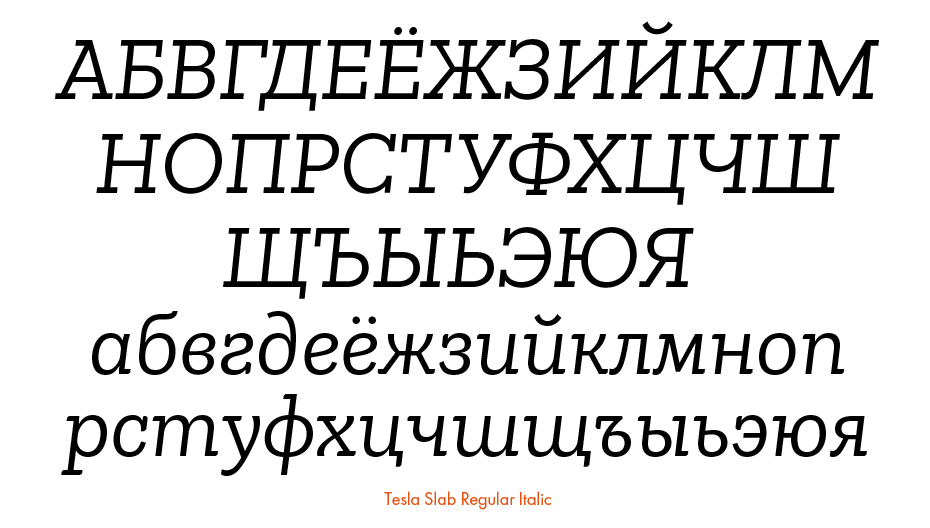
13 потрясающих шрифтовых трендов 2023
То, что вы пишете, важно, но то, как вы это делаете, еще важнее. Типографика — мощный инструмент в руках дизайнера: используйте его правильно, и все обратят внимание, используйте неправильно, и люди просто прокрутят страницу вниз. И хотя навыки проектирования и вкус играют в успехе проекта основную роль, следить за тенденциями важно, нравится вам это или нет. Сегодня мы рассмотрим трендовые шрифты и стили типографики — они уже здесь, и они определенно останутся с нами до конца 2023 года.
Источник: DribbbleЧто такое типографика и почему она важна?
В двух словах, типографика — это то, как ваш текст выглядит на странице/экране/где бы он ни находился. Это искусство настройки различных деталей — шрифта, его размера, длины строки, межстрочного и межбуквенного расстояния — таким образом, чтобы все выглядело аккуратно, привлекательно и передавало нужное настроение.
И дело не только в том, чтобы сделать что-то красивое.
Типографика играет важную роль или, на самом деле, даже четыре важные роли:
- Типографика задает тон и настроение. Она передает сообщение и вызывает эмоции, так же как изображения и цвета.
- Типографика влияет на читабельность и доступность. Может облегчить чтение и восприятие текста, особенно для людей с нарушениями зрения или дислексией.
- Типографика является неотъемлемой частью брендинга и фирменного стиля. Она помогает сделать образ компании, продукт или услугу узнаваемыми и запоминающимися.
- Типографика улучшает UX. Понятный, разборчивый текст помогает пользователю ориентироваться в контенте и воспринимать его.
Горячие тренды типографики в 2023 году
1. 3D-типографика
3D-типографику нельзя назвать чем-то новым: она существует с 60-х годов, но растущая популярность виртуальной и дополненной реальности дала ей новую жизнь.
Мы любим ее, поскольку она добавляет тексту глубину и объем — буквы будто выпрыгивают из экрана.
3D-типографика потрясающе смотрится как в анимированных видео, так и на обычном однотонном фоне. Она привлекает внимание пользователей, но не перегружает дизайн. Самое главное — здесь нет правил. При наличии базовых навыков и соответствующего программного обеспечения вы можете сделать любой шрифт трёхмерным.
Пример трехмерной типографики. Источник Uprock.2. Пиксельные шрифты
Больше чем 3D мы любим только 2D. Пиксельное искусство пришло к нам из первых 2D-видеоигр, поэтому неудивительно, что ностальгическая волна вновь сделала его актуальным. 8-битная ретро-эстетика может придать вашему дизайну игривый причудливый вид — да, такое решение подходит не для каждого проекта, но многие веб-интерфейсы и цифровые продукты лишь выиграют от добавления олдскульной атмосферы. С помощью пиксельных шрифтов вы можете вызвать чувство ностальгии и на несколько мгновений перенести вашу аудиторию в старые добрые времена.
3. Психоделия
Невозможно представить себе 70-е без психоделической эстетики. Этот стиль, вдохновленный галлюцинациями (возникающими вследствие приема психоактивных веществ), подарил миру живые сюрреалистические произведения искусства, для которых характерны смелые, яркие цвета, замысловатые узоры и оптические иллюзии.
В таких работах часто встречается эффект калейдоскопа, когда изображения смещаются и смешиваются друг с другом в завораживающих потусторонних композициях. Этот тренд добрался до шрифтов: но в отличие от классической психоделии буквы в них выглядят не тревожно, а ярко и интересно.
Пример психоделической типографики. Источник.4. Искаженные шрифты
Если психоделические шрифты могут привнести в ваш дизайн ощущение “все будет хорошо”, то искаженные шрифты способны быстро превратить его в «на самом деле все может быть плохо». Такая типографика создает меланхоличную атмосферу, добавляет в проект бунтарский дух, хаос или беспорядок, что довольно эффективно, если ваш бренд ориентирован на молодую аудиторию и отличается дерзким характером.
Искаженные шрифты могут принимать разные формы: выглядеть растянутыми, сжатыми или перекошенными. Буквы становятся неровными, а образующие их штрихи неравномерными. Этот стиль применим как к шрифтам с засечками, так и к шрифтам без засечек, а искажение может быть любым — от еле заметного до экстремального. Просто попробуйте приручить этот тренд — это нелегко, но оно того стоит 😉.
Примеры искаженных шрифтов. Источник.5. Курсив
Просто курсив? На самом деле такая типографика создает ощущение движения, добавляет в дизайн драматизма или элегантности — всё зависит от выбранного шрифта. Курсив позволяет сделать акцент на том или ином слове/фразе и выделить важную информацию, что особенно актуально, когда вам нужно уместить в интерфейсе много текста.
Да, курсив может показаться скучным. Но попробуйте поэкспериментировать с углом наклона и другими настройками, и вы получите уникальную инновационную типографику, которая добавит в дизайн игривую или художественную нотку.
Сочетайте курсивные шрифты с контрастными начертаниями или стилями, например, жирные и тонкие, и вот он — поразительный визуал, притягивающий взгляд.
Clermont Arms2017
Предоставлено Киллианом Уолшем
Газовое кафе и бар.
2020Эса Халланоро
Плакат Coors «Phone Home»1982
Джек Граймс
Канцтовары для ресторанов Ombra2018
Carlos Cocktail Barc. 2019
Витрина магазина Le Week-Endc. 1965
Столовая и бар Rosella2019
Nepomuk Bar2019
Taza Flores2019
Taverne Tour 20 19в.